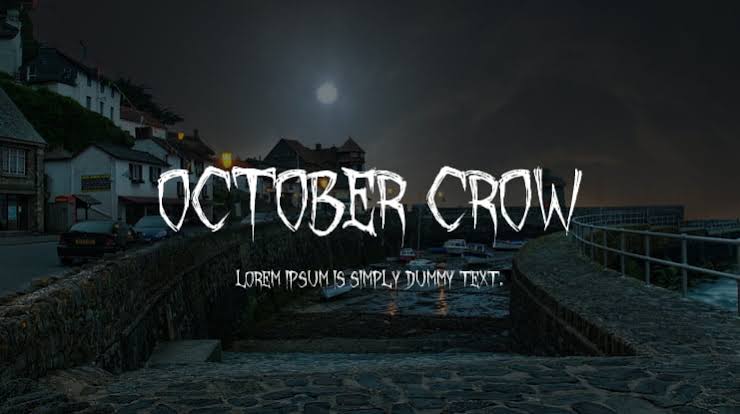
Tema desain akan menciptakan nuansa, mood dan pesan yang berbeda, karena menggunakan elemen visual yang bervariasi pula. Gaya font salah satu elemen visual yang perlu dipilih juga berdasarkan tema desain grafis terutama untuk jenis desain poster atau konten. Untuk tema desain poster seperti musim gugur dan halloween, gaya font yang digunakan cukup berbeda meski waktunya bersamaan.
Desain poster untuk tema musim gugur dan halloween memiliki gaya font berbeda karena menyesuaikan dengan mood tema tersebut. Font halloween akan dipilih untuk tampil nyentrik, horor dan misterius. Berbeda dengan font poster untuk musim gugur yang menggunakan gaya elegan dan berkesan alami.
FONT TEMA MUSIM GUGUR
Desain poster untuk tema musim gugur umumnya identik dengan warna hangat seperti cokelat, oranye dan kuning. Seringkali desain musim gugur ingin tampil elegan sehingga kerap menggunakan gaya font script dan brush. Font bergaya alami akan cocok mencerminkan kesan hangat pada tems poster musim gugur.
Autumn in November
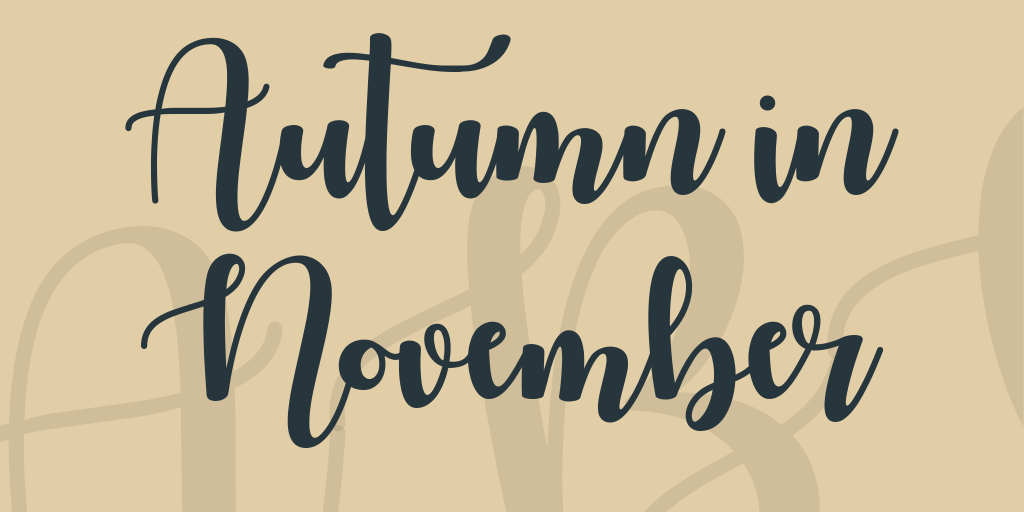
Font bergaya tulisan tangan yang elegan dan ramah tersebut akan cocok untuk tema desain musim gugur. Desain poster musim gugur sering menggunakan elemen visual seperti gambar daun dan pumpkin sehingga tampil alami.
Untuk itu penggunaan font bergaya alami seperti font autumn in november akan sangat cocok. Font tersebut dapat memberikan desain kesan hangat dan natural karena garis-garis huruf yang alami seperti tulisan tangan.
Harvest Barn
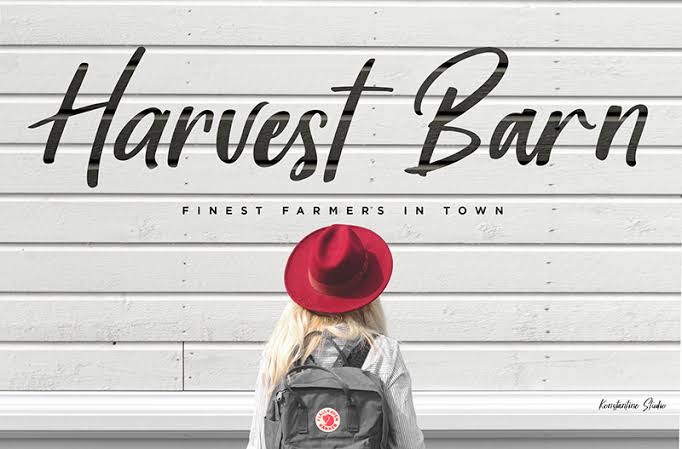
Selain gaya font script latin, font script brush juga memiliki kesan alami dan tampil menawan. Font ini juga cocok untuk mencerminkan kesan alami dan hangat pada tema poster musim gugur. Desain musim gugur dengan font harvest barn yang sederhana ini juga bisa menciptakan kesan vintage.
Cocok jika desain poster ingin tampil tradisional dan vintage namun bergaya musim gugur bisa menggunakan font ini. Selain itu garis huruf terlihat alami sehingga akan relevan dengan tema musim gugur.
Falling Leaves
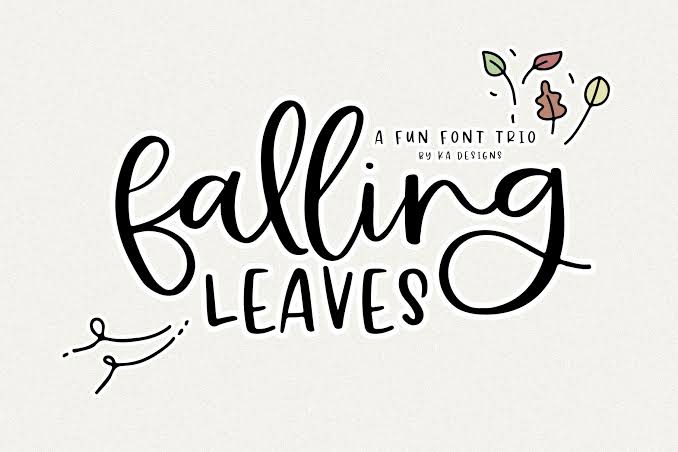
Gaya font ini juga memiliki style huruf latin yang elegan dan ramah, cocok untuk mencerminkan tema musim gugur. Jenis font ini termasuk script dekoratif karena hurufnya memiliki dekorasi. Gaya huruf dalam font ini tidak hanya terlihat alami tetapi juga mencerminkan daun yang jatuh.
Font falling leaves ini tampil elegan dengan aksen daun musim gugur sehingga relevan dengan elemen seperti daun musim gugur. Untuk desain poster bertema musim gugur dan alam, font ini akan sempurna dan menciptakan kesan alami.
Autumn chant
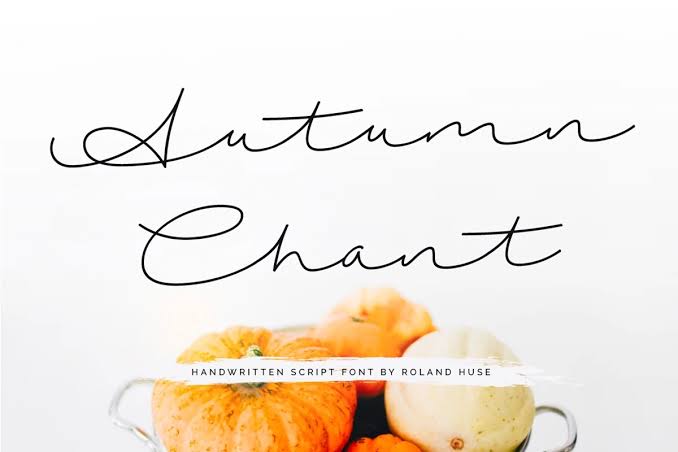
Kebanyakan rekomendasi font untuk tema ini menggunakan gaya script latin yang elegan. Bedanya font satu ini lebih tipis dari falling leaves dan autumn in november. Gaya tulisan tangan pada huruf terlihat seperti autograph, sehingga bisa membuat desain poster musim gugur terlihat elegan dan hangat.
Penggunaan gaya font yang tipis dan elegan ini akan menciptakan poster yang lebih formal. Gaya ini juga cocok digunakan pada desain poster musim gugur yang ingin tampil minimalis dan sederhana tetapi masih elegan.
Maple Memories
Jenis font poster musim gugur ini menggunakan gaya modern calligraphy, yang masih termasuk font family script. Huruf latin bersambung menciptakan kesan elegan dengan hurufnya yang masih tebal dan terbaca dengan baik. Gaya huruf yang tebal dan melengkung menciptakan kesan alami dan ramah.
Tidak seperti autumn chant yang lebih formal, font ini akan menciptakan poster yang ramah dan menyenangkan. Font ini memiliki gaya lebih kasual dan hangat, sehingga akan menciptakan poster dengan suasana santai dan nyaman.
FONT UNTUK TEMA HALLOWEEN
Jika font untuk poster musim gugur tampil elegan dan alami, berbeda dengan font halloween yang tampil seram dan unik. Gaya font brush yang memiliki tekstur dan tidak halus akan menciptakan kesan horor dan misterius. Berikut ini beberapa font yang direkomendasikan untuk font halloween:
Creepster
Font Halloween biasanya terkenal dengan style huruf yang horor dan seram seperti font creepster. Jenis font ini termasuk gaya klasik yang terinspirasi dari film-film horor atau seram lama. Hurufnya sedikit tebal dan terlihat seram karena tidak halus tapi bergerigi yang tak beraturan.
Bentuk gelomebang atau gerigi dalam hruufnya terlihat menyeramkan dan seolah mencerminkan darah. Gaya font ini cocok untuk tema desain poster halloween dan gunakan sebagai headline. Meski unik dan seram, hurufnya masih mudah terbaca dengan baik.
Nightmare 5
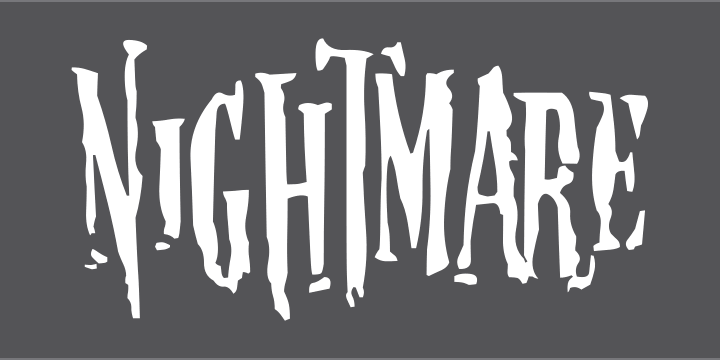
Font bergaya horor untuk tema halloween seringkali menggunakan huruf yang tajam dan memiliki efek distorsi agar terlihat semakin menyeramkan. Gaya dalam font nightmare terlihat menyeramkan tajam dengan bentuk huruf yang tidak beraturan. Efek distorsi dan bentuk huruf yang tak beraturan menambahkan kesan horor dan misterius.
Untuk digunakan dalam desain poster bertema musim gugur dan halloween sebaiknya memilih gaya elemen yang relevan dengan tema. Gaya font yang cocok untuk musim gugur lebih cenderung elegan dan alami, berbeda dengan halloween yang berkesan menyeramkan dan unik. Meskipun masih dalam rentan musim yang sama, tema desain dapat cukup berbeda bergantung pesan dan suasana yang ingin diciptakan. Beberapa rekomendasi font yang cocok digunakan untuk tema halloween dan musim gugur bisa menciptakan suasana yang tepat.